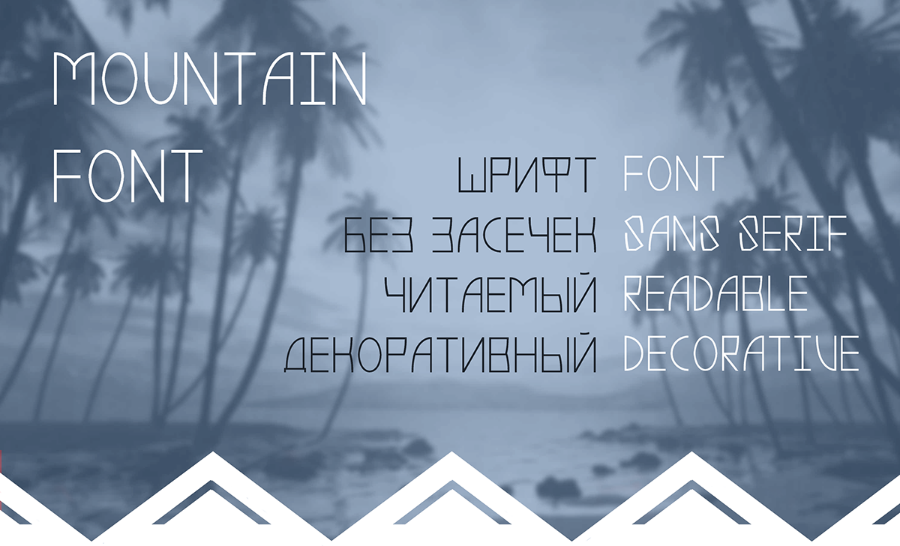
Aqui está uma versão em português do Brasil para a descrição da fonte Mountain Font, seguindo os requisitos fornecidos: Esta é a minha primeira experiência criando uma fonte. Decidi compartilhar meu resultado com todos vocês. Trabalhei numa sans serif, simples e moderna que, na minha opinião, combina perfeitamente para qualquer projeto web ou impresso. Encontrei um pequeno glitch durante o desenvolvimento, então fui em contato diretamente contigo. Peço desculpas pelo problema e lhe ofereceria algum incentivo financeiro caso você não tenha problemas com isso. A solução de problemas é sempre um bom aprendizado e acreditamos que podemos tornar este projeto ainda melhor. Caso queira colaborar, as formas de pagamento disponíveis são WebMoney: WMR R235087555461 ou WMZ Z357659124389. A Mountain Font é uma sans serif pura e limpa, ideal para estilos simples e contemporâneos. O designer, Hamilton, conseguiu capturar a essência da fonte de maneira incrivelmente criativa, oferecendo um conjunto de recursos versáteis que se encaixa perfeitamente em qualquer projeto design.